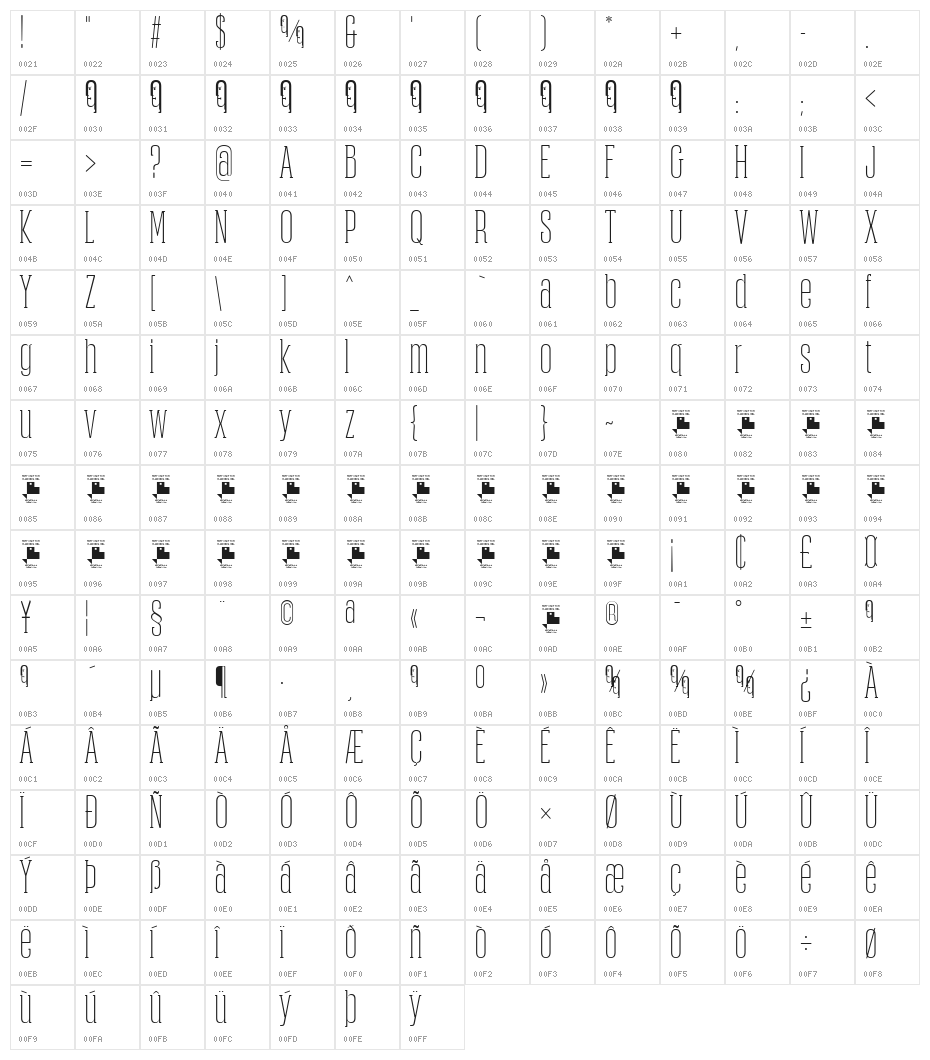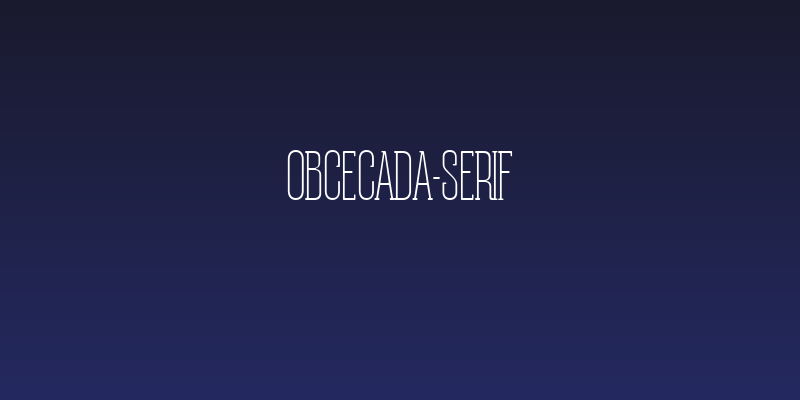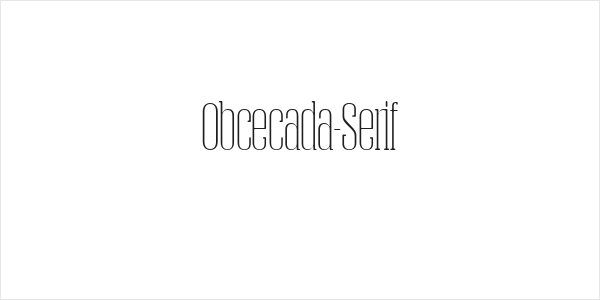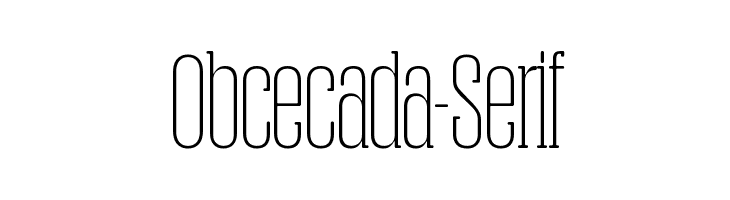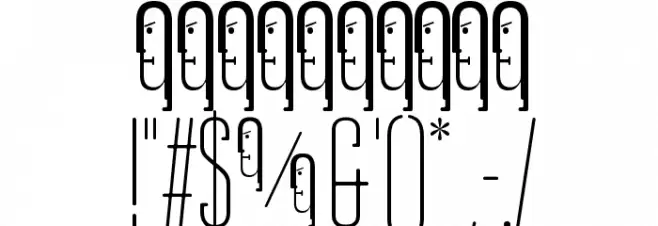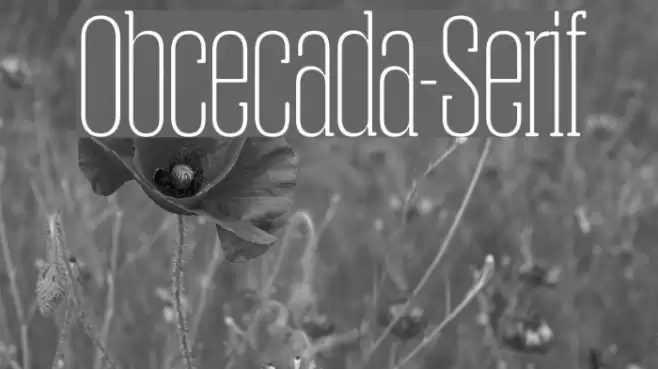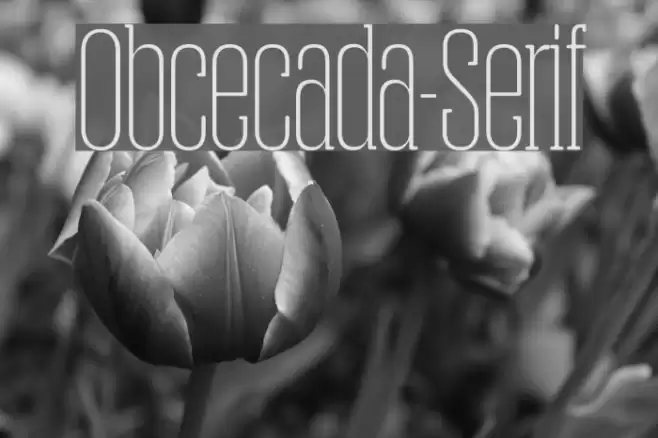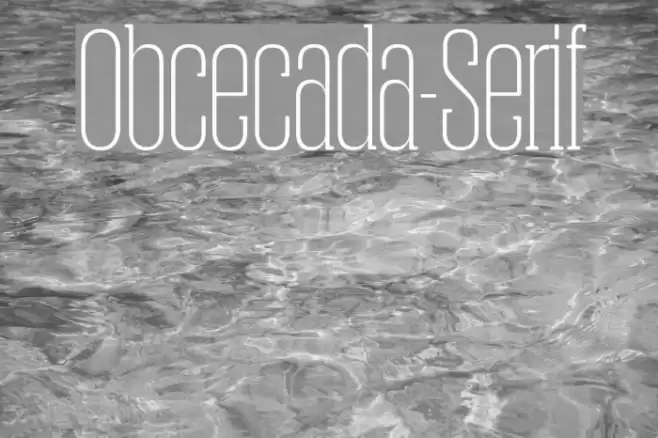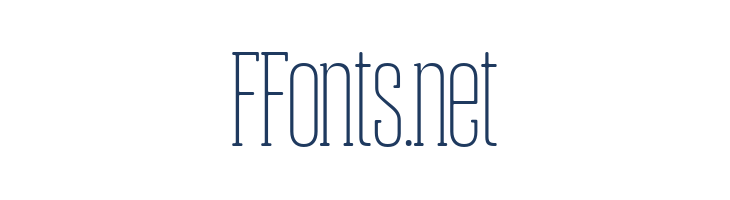
Obcecada-Serif Font
✎ Serif
| श्रेणियाँ | Serif |
| चौड़ाई | Condensed |
| उपयोग का मामला | Headlines, Logos |
| सुझाए गए प्रोजेक्ट | Ideal for fashion magazines, luxury branding, artistic posters, and elegant invitations. |